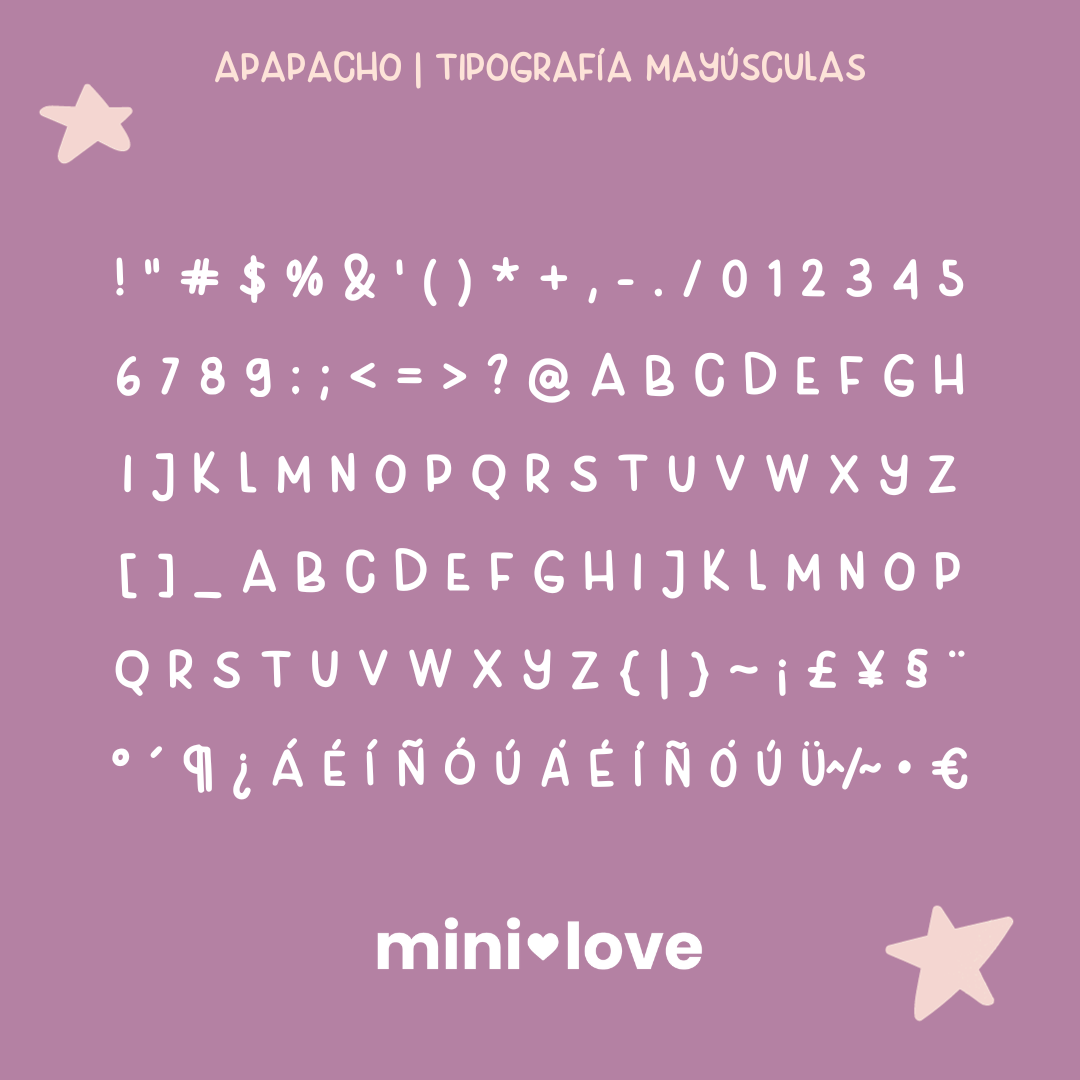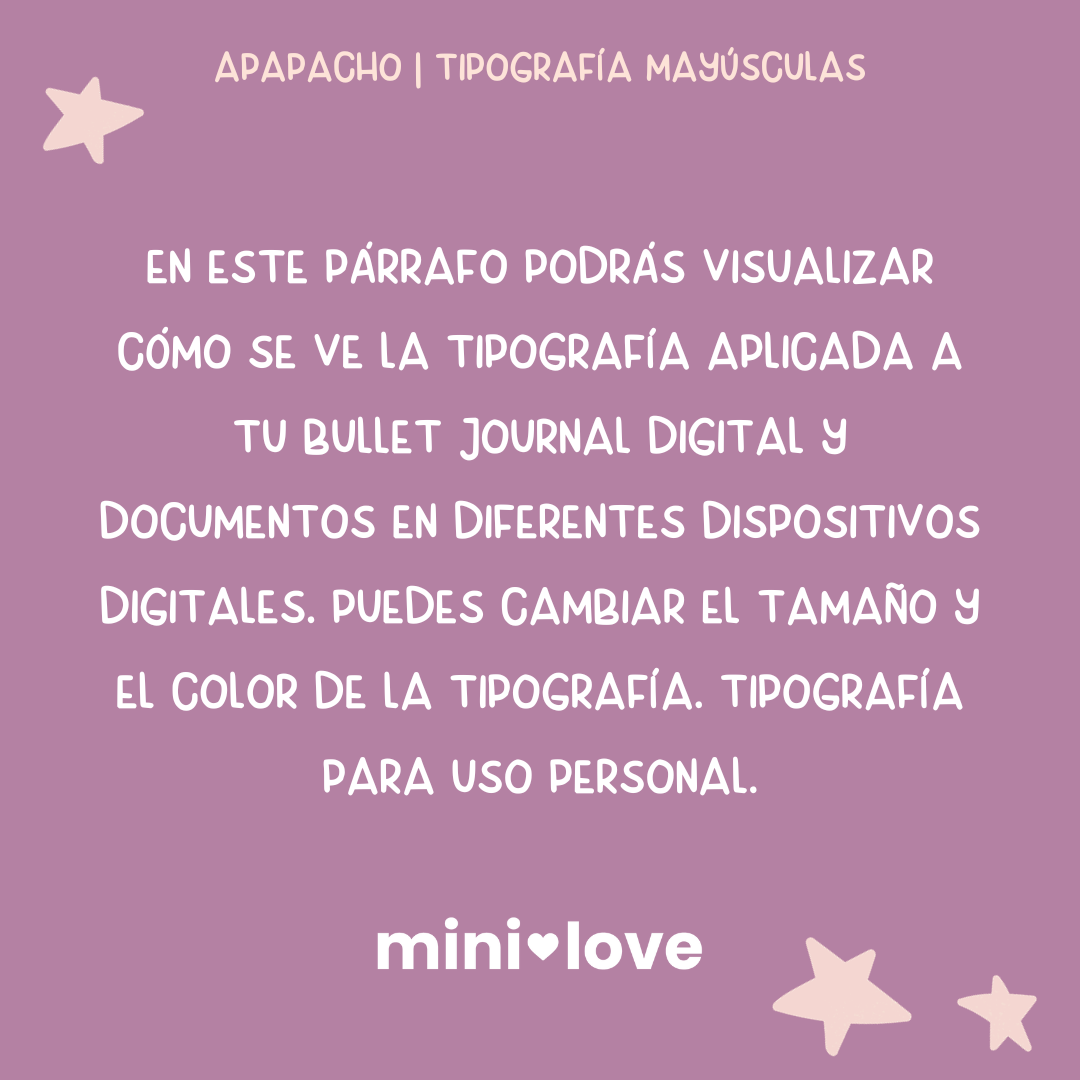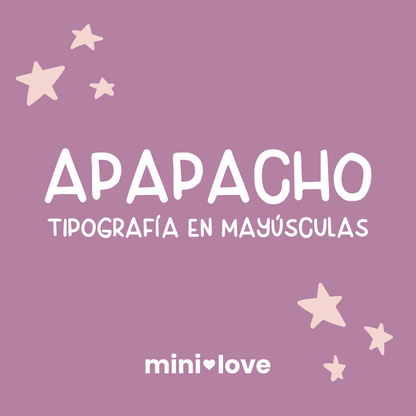
Tipografía Apapacho
Esta tipografía estilo manuscrito en mayúsculas es la elección perfecta para darle un toque personal a los títulos de tu bullet journal, apuntes y anotaciones. Transforma tus escritos en una experiencia única, como si estuvieras escribiendo con tu propia caligrafía.